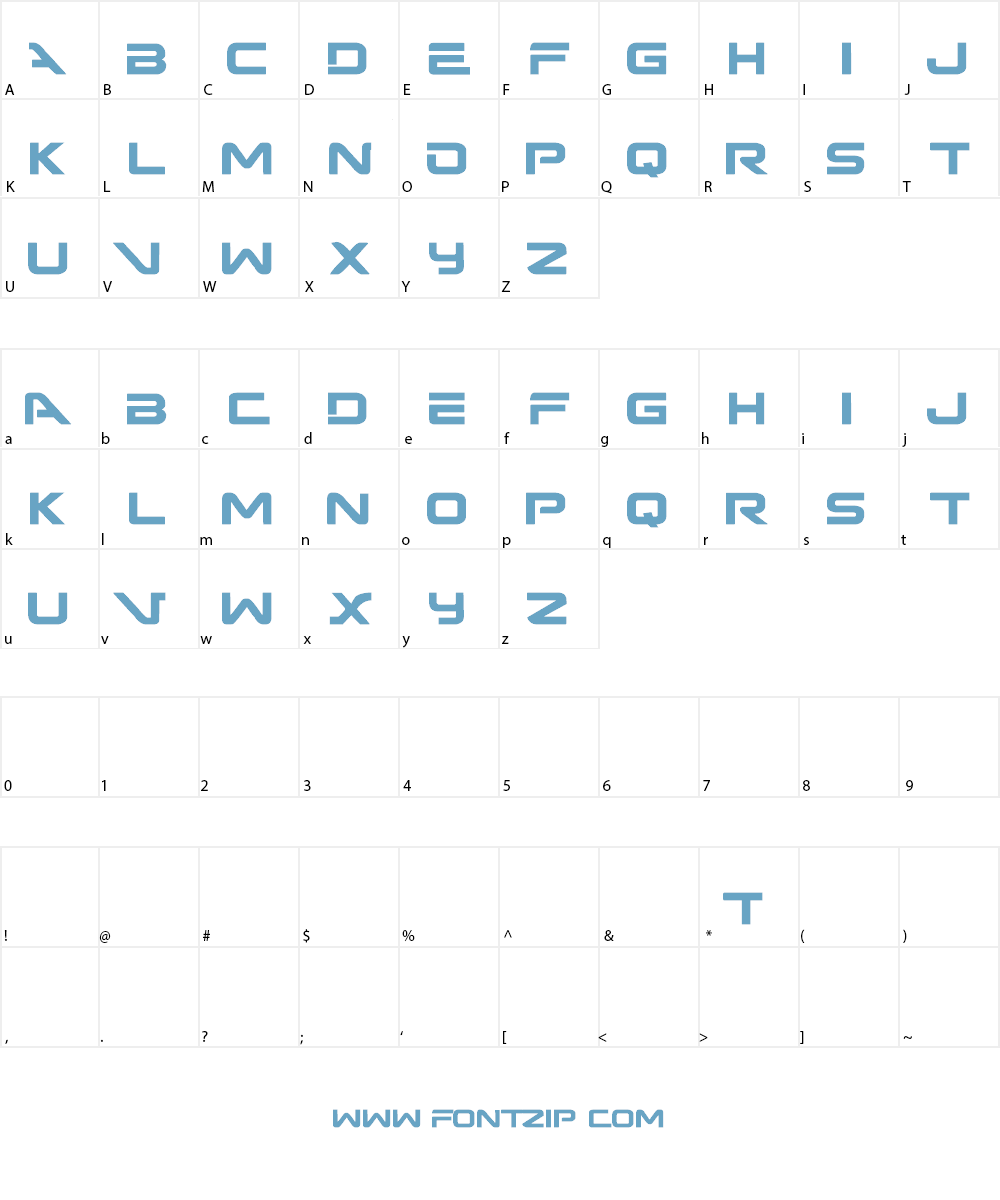
Una tipografia diseñada realizada de la película TERMINATOR: DARK FATE
Nota: para dark fate es la tipógrafía FUTURA EXTRABLACK o BLACK
otra cosita. usar * para la letra "t"